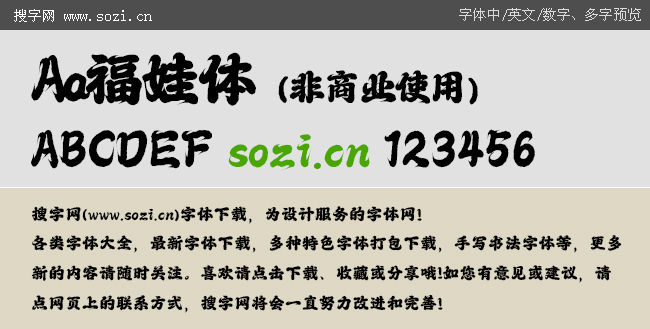
Aa福娃體
搜字網(wǎng)給大家提供一款A(yù)a福娃體(非商業(yè)使用)中文字體下載,Aa福娃體是一款國風(fēng)手書字體,,該字體筆畫隨性,連筆較重,結(jié)構(gòu)肆意灑脫,具有很好的視覺感。適合應(yīng)用于藝術(shù)設(shè)計(jì)、平面宣傳設(shè)計(jì)、網(wǎng)頁設(shè)計(jì)、海報(bào)設(shè)計(jì)等應(yīng)用(此字體為個人非商用版,商用可以聯(lián)系QQ:1006760504)。